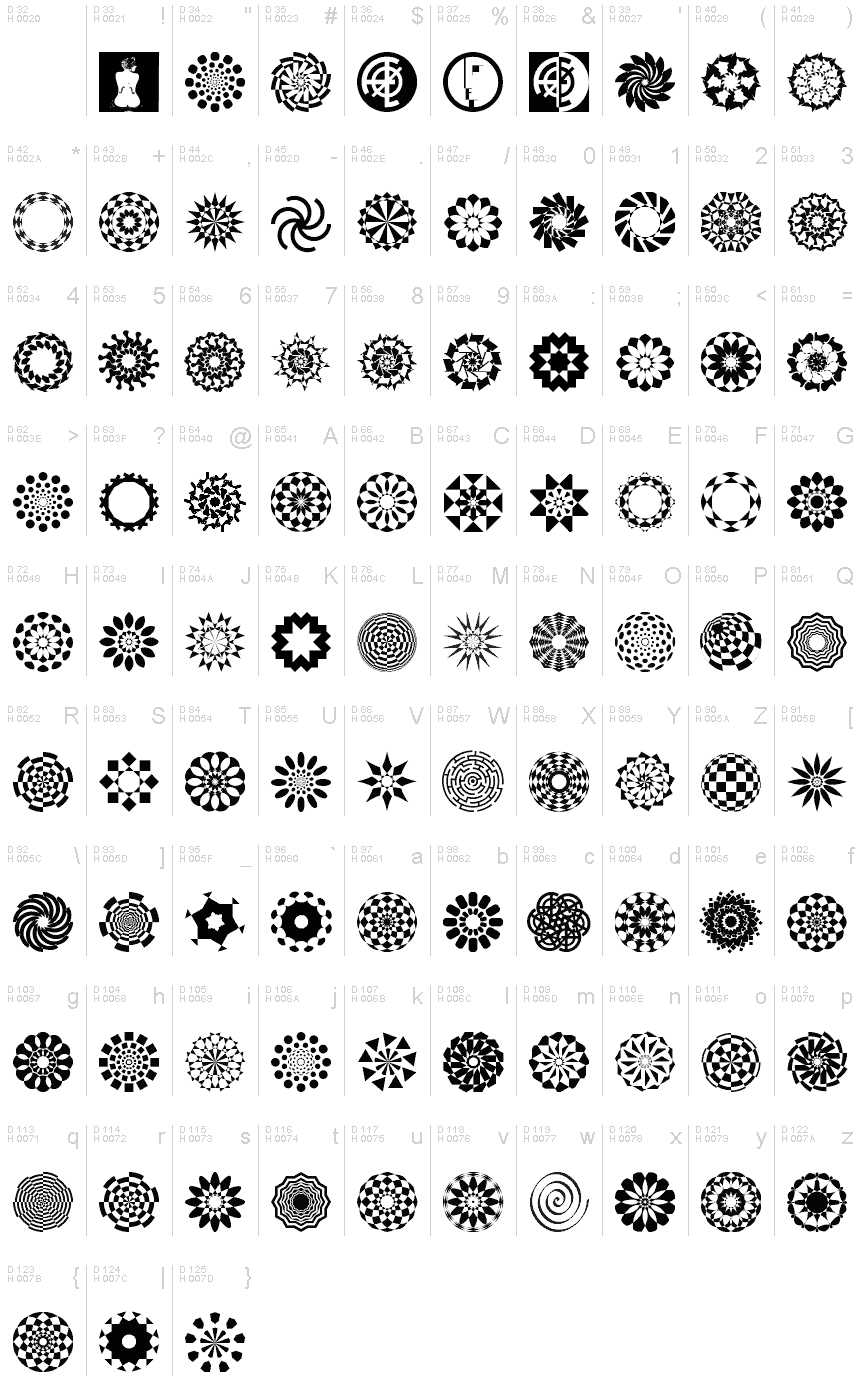
Wach Op-Art
95 Clip art in a font!
Esta coleccin de Clip art ha nacido de formas geomtricas bsicas y complejas movindose y girando sobre el crculo, inspirada tambin en los diseos de la coleccin de relojes de diseo y ms concrtamente a la serie Op-art creada por m al final de los 80.